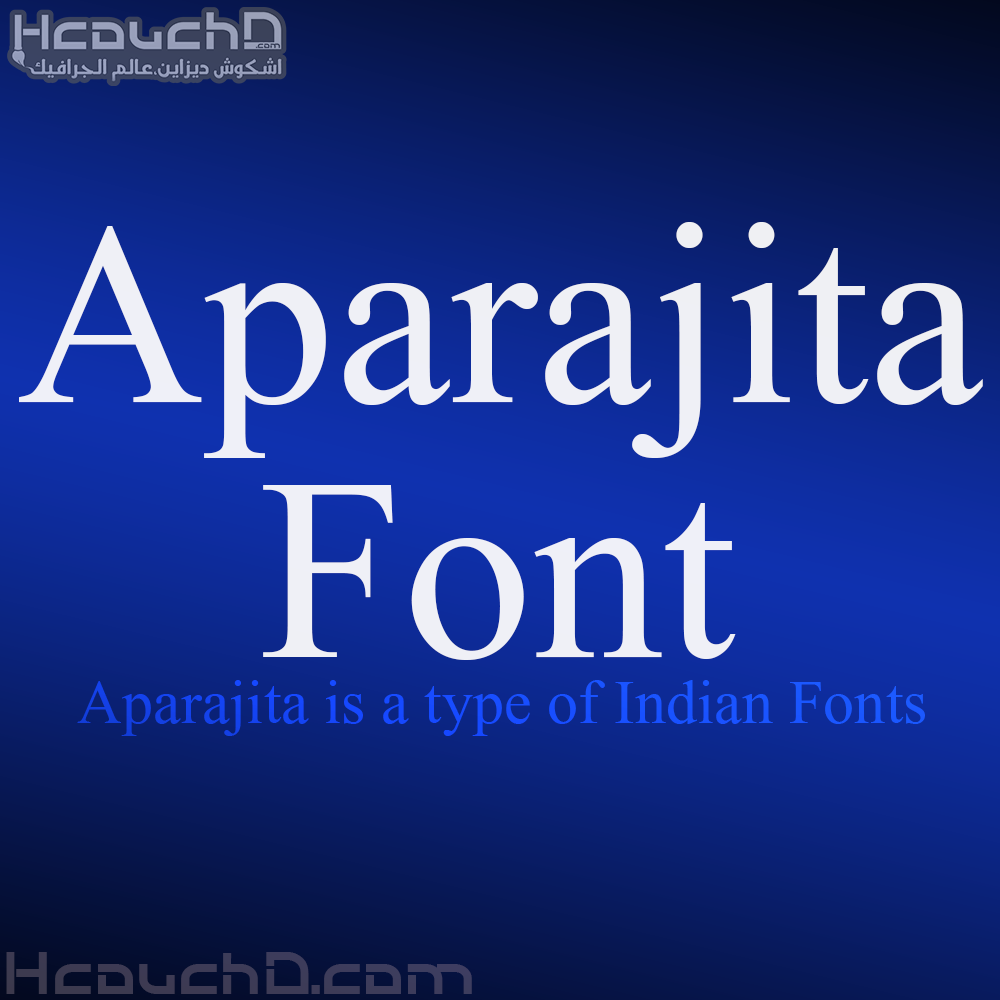
خط Aparajita هو نوع من الخطوط الهندية ، و سبق أن استعملناه في درس ” درس 34 : كيفية عمل تأثير خط مجمد بالفوتوشوب + ملف PSD” ، يمكنك تحميل هذا خط من رابط أسفله …